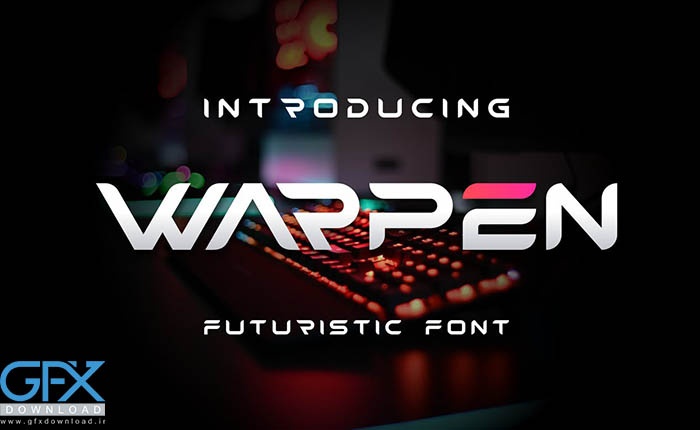
دانلود رایگان فونت Warpen
دانلود فونت Warpen
دانلود رایگان فونت انگلیسی Warpen
می توانید برای طراحی مارک یا برند تجاری،طراحی کارت ویزیت،پوستر،کارت دعوت و سایر موارد دیگر از این فونت زیبا استفاده نمایید. دانلود رایگان فونت Warpen یک فونت نمایشگر برجسته و معتبر است. این فونت برای هر پروژه برندسازی مانند لوگو، چاپ تی شرت، esport و بسیاری موارد دیگر مناسب است. برجسته در طیف گسترده ای از زمینه ها.
فونت انگلیسی Warpen